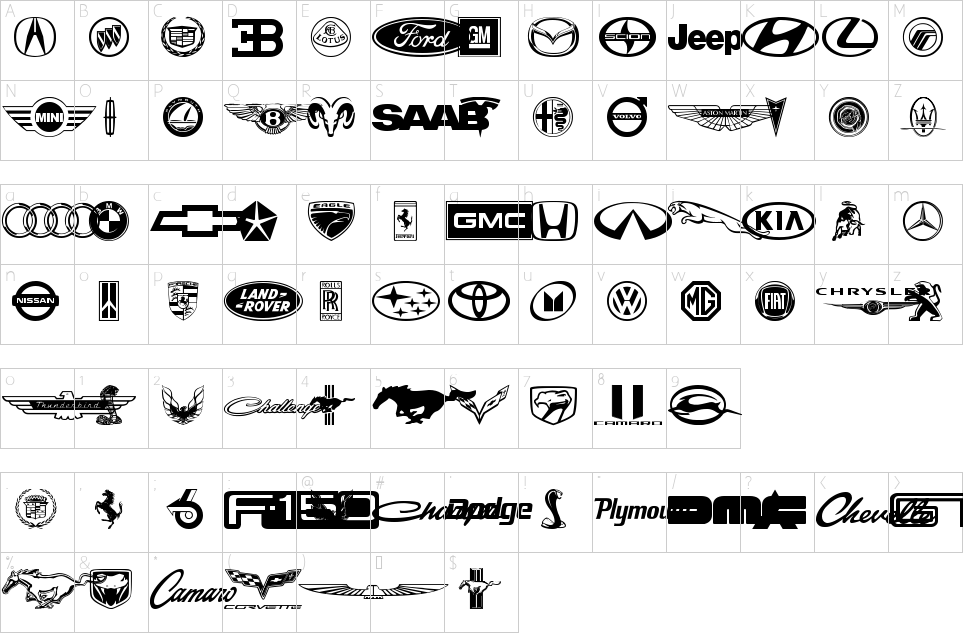
A Motorama Font é uma elegante e sofisticada opção para designers que estão buscando uma fonte moderna para seus projetos de design gráfico. Especificamente projetada para os profissionais de design gráfico que buscam uma fonte com um visual sóbrio e versátil, a Motorama se destaca pelo seu equilíbrio perfeito entre modernidade e elegância. Esta fonte foi criada por Iconian Fonts e, embora a fonte tenha sido visualmente avaliada por um designer invisível, seu design atende perfeitamente aos requisitos de uma fonte que pode ser usada em uma variedade de projetos, desde materiais de marketing até elementos de design gráfico digital. Mais de 20.204 pessoas já baixaram a Motorama Font para fazer parte de seus projetos, demonstrando a sua grande aceitação e popularidade. Em um mundo cada vez mais digital, a Motorama é uma escolha conveniente para designers que buscam uma fonte de qualidade que se adapta à sua necessidade de se destacar entre o resto.